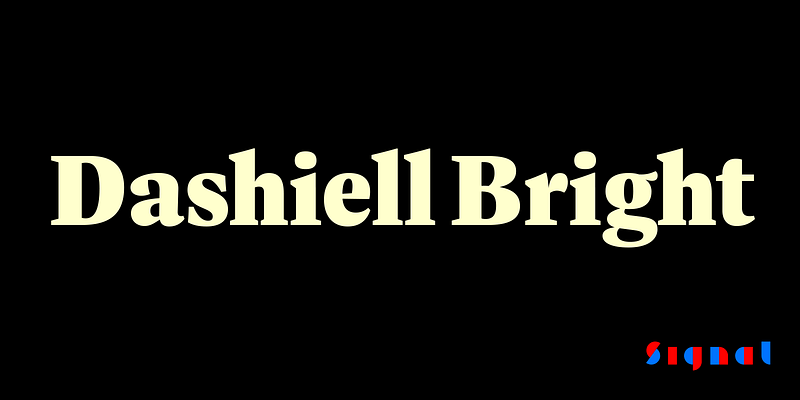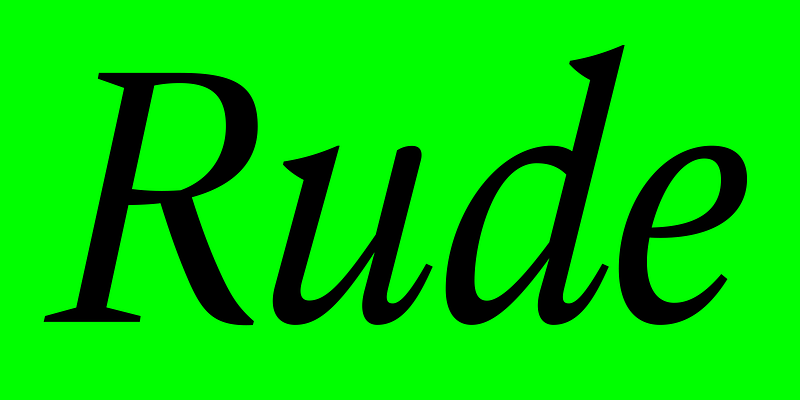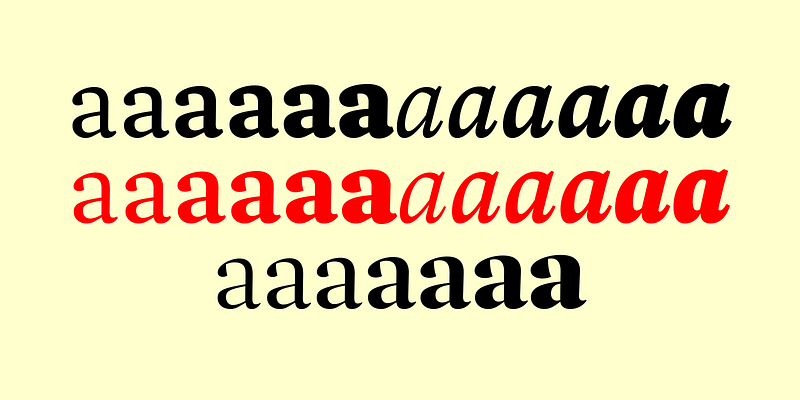
Dashiell Bright hat mehr Glanz als Dashiell Text, mit subtil feineren Haarlinien und Serifen, und eignet sich besonders für gedruckte Bücher und Zeitschriften, wo ihre scharf gezeichneten Formen auf der Seite gut zur Geltung kommen, ohne aufdringlich zu sein. Sie ist zwar etwas literarischer als Dashiell Text, verfügt aber über dieselben sechs Schriftstärken, großzügige Versalien und x-Höhen sowie Keilserifen ohne Klammern.